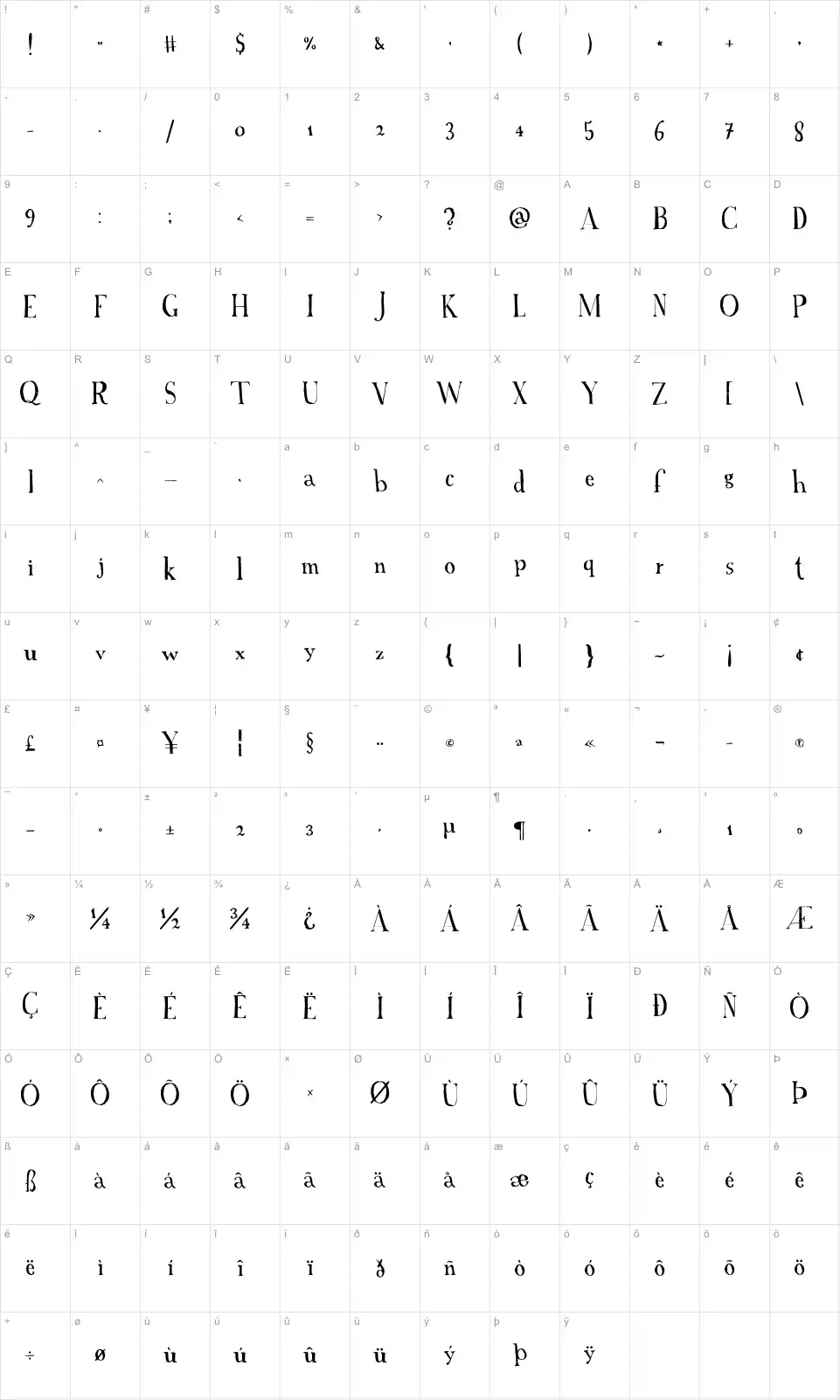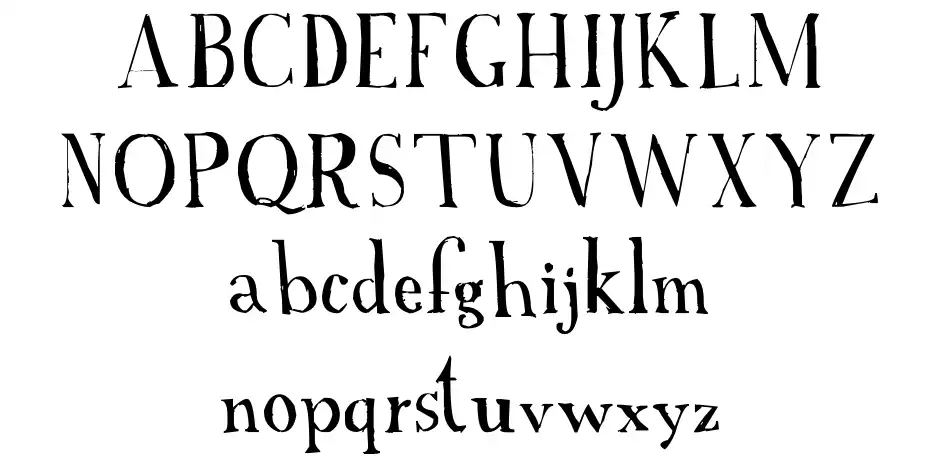
A Font with Serifs – Fonte Grátis
A Font with Serifs
A fonte A Font with Serifs, criada pelo designer Extate, é um recurso gráfico cheio de personalidade e elegância. Se você está procurando por uma fonte com serifos para um design de texto mais sofisticado, esta é a escolha perfeita. Se você quiser experimentar o aspecto da fonte sem comprometer a versatilidade, pode baixá-la ou gerar um preview personalizado de texto online para ver como ela se encaixa em seus projetos antes de usá-la. Esta font, que pertence à categoria Fancy e categoria de acabamento erodido, está disponível sob uma licença free e pode ser baixada em formato TTF. Com um tamanho de 86 KB e mais de 1495 downloads, ela oferece uma excelente qualidade e versatilidade para qualquer projeto gráfico. Você pode conhecer mais sobre a fonte e o designer no site http://www.extate.lt.